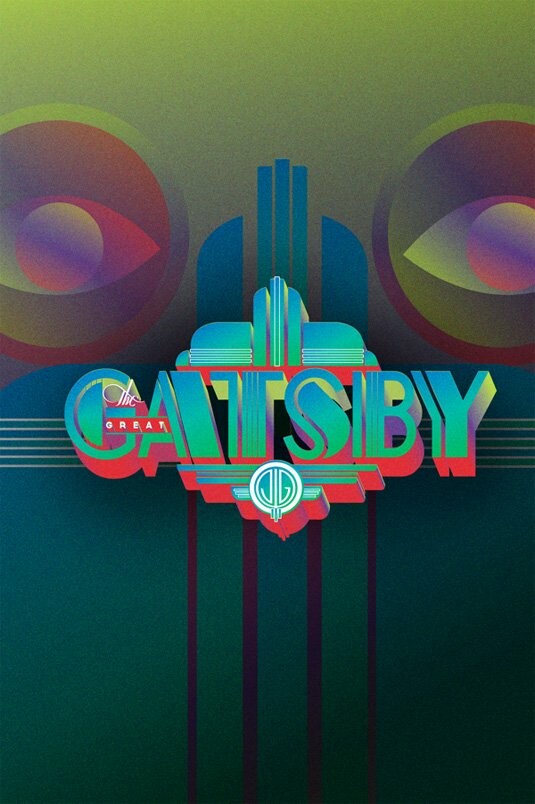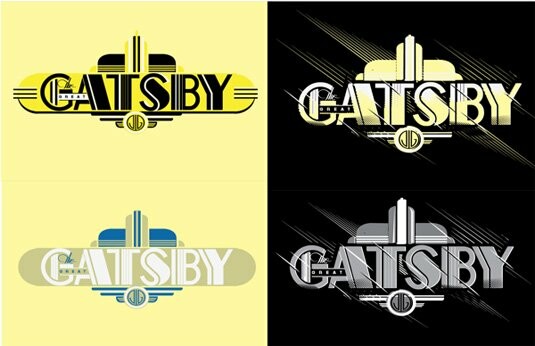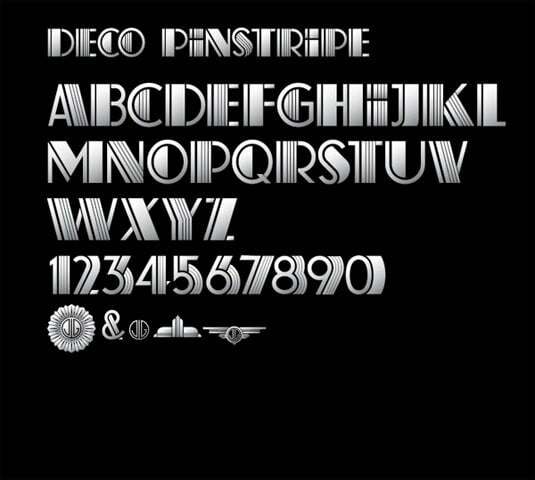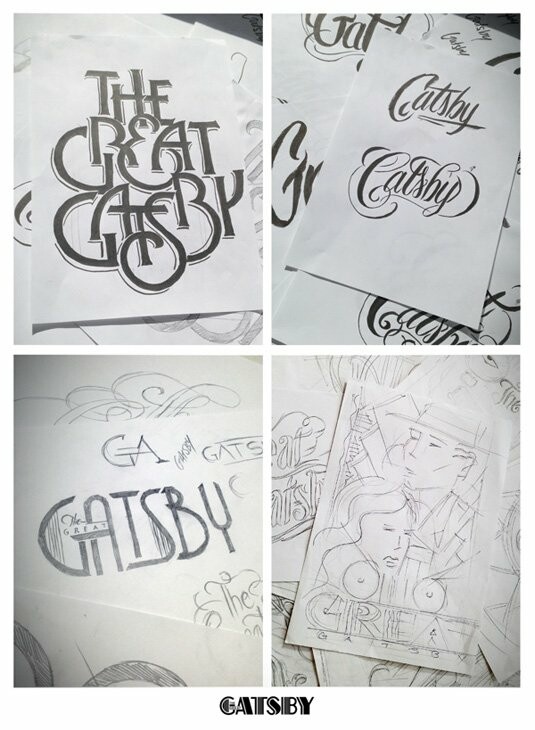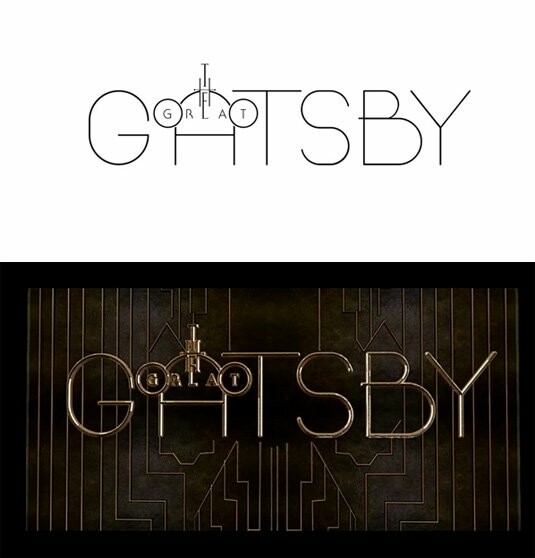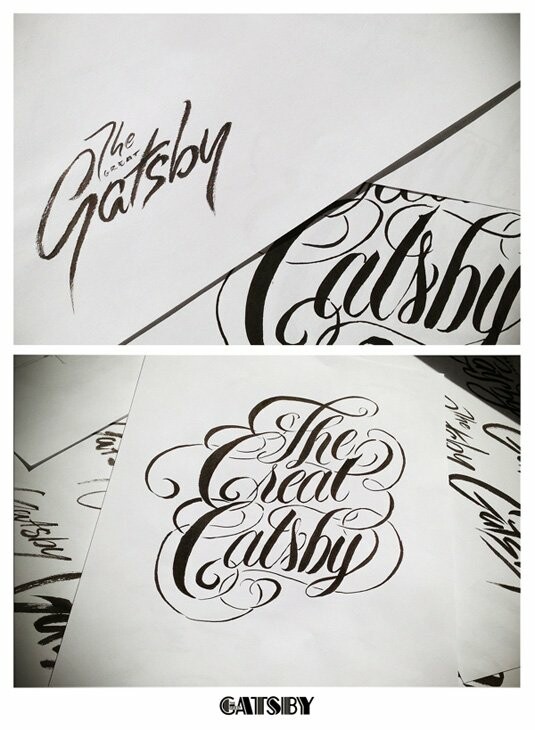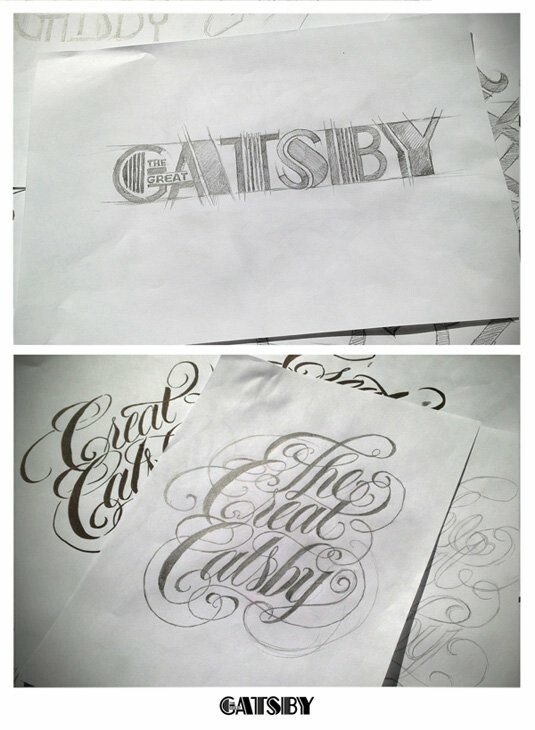
H Υπέροχη τυπογραφία πίσω από το The Great Gatsby .
Ενώ οι κινηματογραφικές αίθουσες συνεχίζουν ακόμα να γεμίζουν για τον Υπέροχο Γκάτσμπι του Baz Luhrmann, και άπειρο μελάνι έχει χυθεί για τα σκηνικά ή τα κουστούμια της ταινίας, λίγο φαίνεται να έχουμε σταθεί ως τώρα στην καταπληκτική κι εμβληματική γραφιστική που συνοδεύει την ταινία της χρονιάς.
Το ξεχωριστό του συγκεκριμένου artwork, που δημιουργήθηκε αποκλειστικά για την τελευταία μεταφορά στον κινηματογράφο του ξακουστού μυθιστορήματος του Σκοτ Φιτζέραλντ, δεν είναι παρά η εντυπωσιακή χρήση της τέχνης της τυπογραφίας ώστε να αντανακλάται όσο το δυνατόν περισσότερο η ατμόσφαιρα της δεκαετίας του 1920'
Το Like Minded Studio, με έδρα το Σύδνεϋ, ήταν το δημιουργικό γραφείο που ανέλαβε το γραφιστικό κομμάτι του φιλμ, με στόχο να πραγματοποιήσει το όραμα του Luhrmann για ένα μοναδικό λογότυπο σε στυλ  Deco, αντιπροσωπευτικό της περιόδου του μεσοπολέμου.
Η γραμματοσειρά του Υπέροχου Γκάτσμπι είναι εμπνευσμένη από το art deco αλφάβητο του KH Schaefer.
Ο σχεδιασμός των τίτλων αρχής και τέλους της ταινίας, καθώς και όλης της γραφιστικής που την συνοδεύει έχει ήδη λάβει διθυραμβικές κριτικές από κοινό και ειδήμονες  κριτικούς..